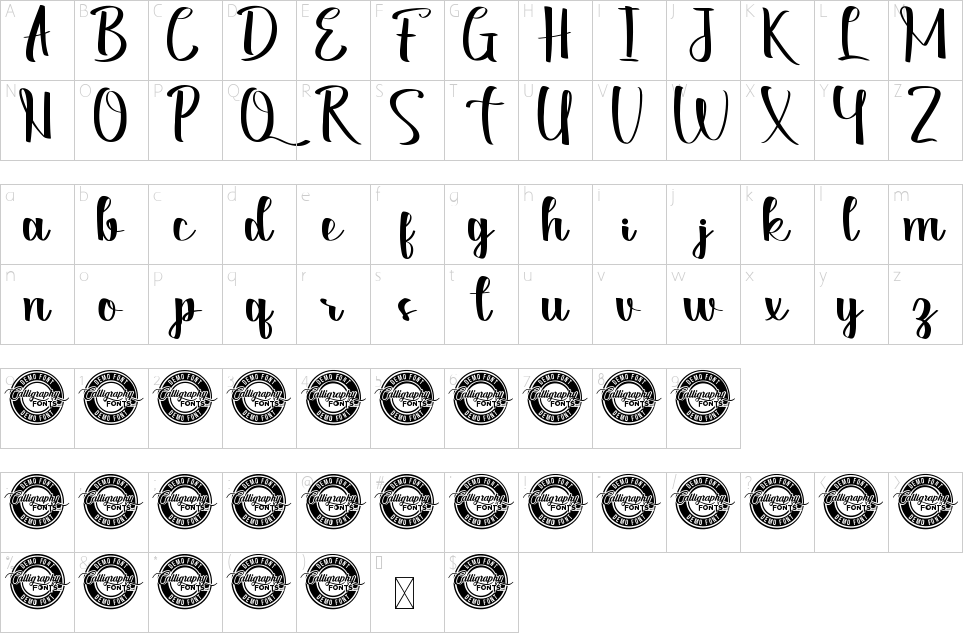
A fonte Anthonyela é uma escolha elegante e moderna para qualquer projeto de design gráfico. Desenvolvida por CalligraphyFonts, esta fonte oferece um toque refinado com suas linhas elegantes e gradativa. Com uma versão compatível tanto para Windows quanto para Mac, Anthonyela está disponível para que você possa incorporá-la em suas criações digitais. A fonte tem se destacado entre os designers ao redor do mundo, sendo baixada 3,601 vezes. Se você está procurando por uma fonte bonita e versátil para seus trabalhos, Anthonyela é uma ótima escolha para adicionar um toque atraente ao seu design.